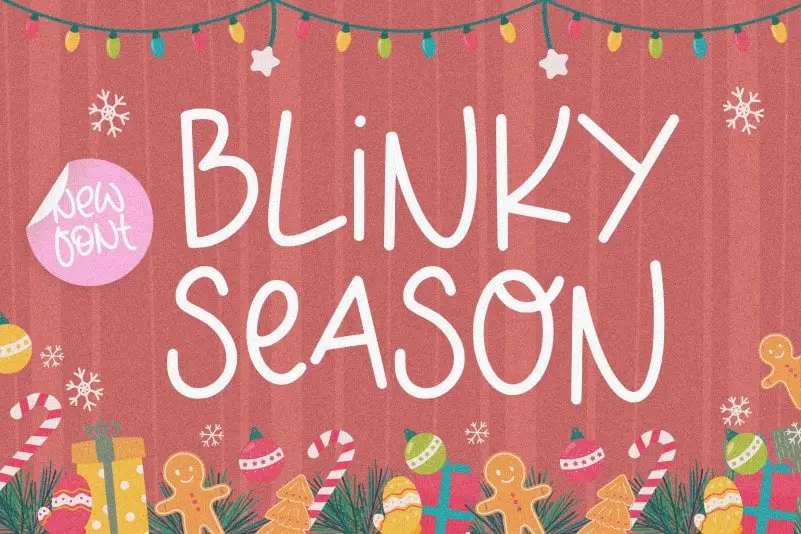
BLINKY SEASON Monoline Font – Download Grátis
A Blinky Season Monoline Font é uma escolha perfeita para aqueles que desejam dar destaque a seus materiais de marca ou publicidade, seja na embalagem de produtos, no projeto de identidade visual, nas revistas, nas redes sociais, até mesmo em anúncios de casamento. Suas linhas retas e modernas permitem uma composição leve e acolhedora que se adequa a qualquer formato ou tamanho de texto, tornando-a uma opção versátil para expressar textos destacados sobre o fundo. Com seu design elegante e minimalista, Blinky Season Monoline é ideal para quem busca transmitir uma identidade visual forte e profissional em seus materiais. A fonte mantém um equilíbrio entre modernidade e sofisticação, permitindo que a sua mensagem seja percebida de maneira clara e eficaz. Este tipo de fonte não só oferece um toque inovador aos seus projetos como também é uma excelente escolha para manter uma consistência estilística, tornando-o uma ótima adição a qualquer coleção de fuentes. Ideal tanto para os iniciantes quanto para os profissionais do design gráfico, Blinky Season Monoline oferece flexibilidade para criar designs que se adequem às suas necessidades e ao seu estilo. Compreender o potencial desta fonte é entender a importância da boa composição visual em sua obra final.